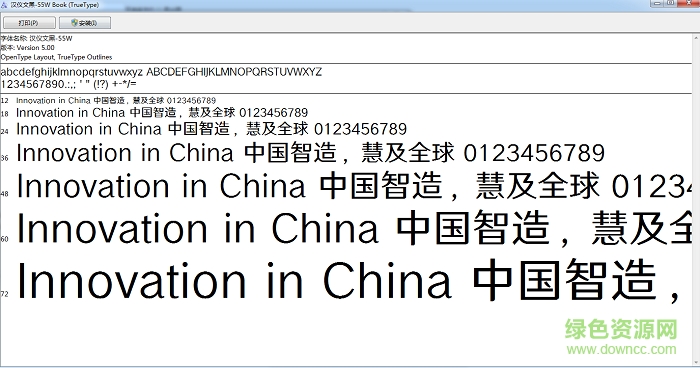
hywenhei-eew字體就是漢儀文黑-55W字體,這款字體粗細(xì)適中,結(jié)構(gòu)嚴(yán)謹(jǐn),大氣工整,比較標(biāo)致,適應(yīng)性較強,可用作海報字體,有需要者歡迎前來下載!
該字體線條非常勻稱,字形端正大方得體,整體效果非常的出色,且字庫完整,可以廣泛應(yīng)用于廣告設(shè)計、宣傳海報、ppt、影視制作以及任何使用文字的領(lǐng)域!